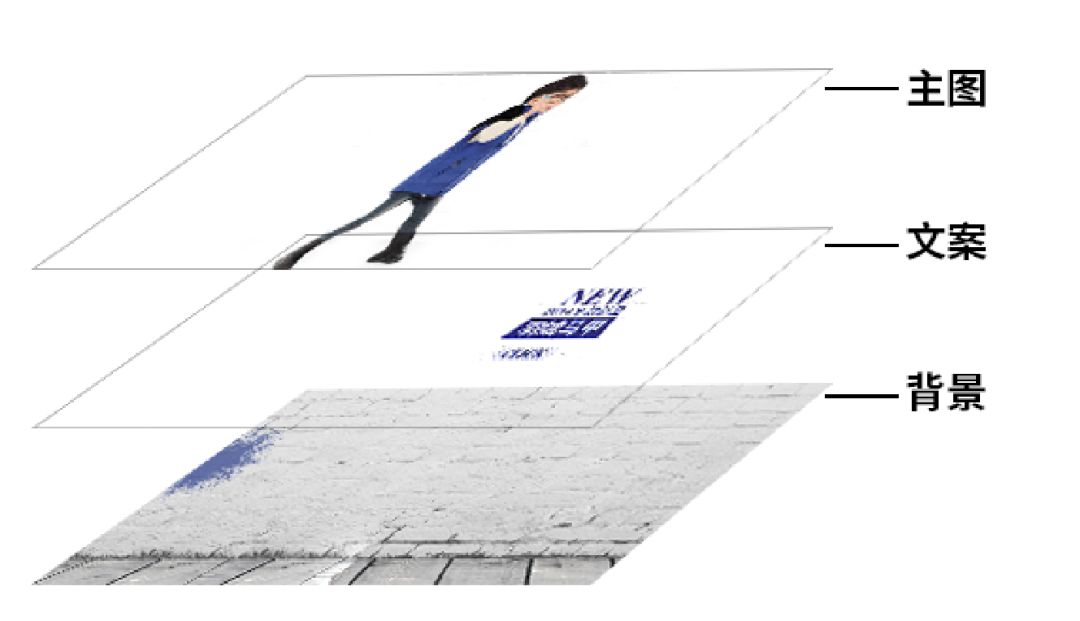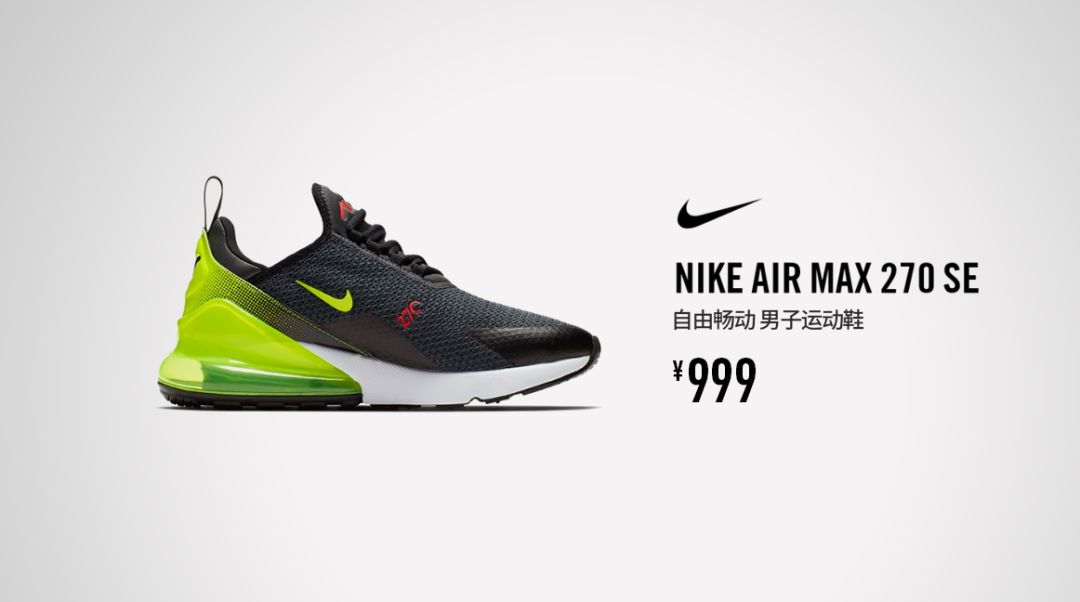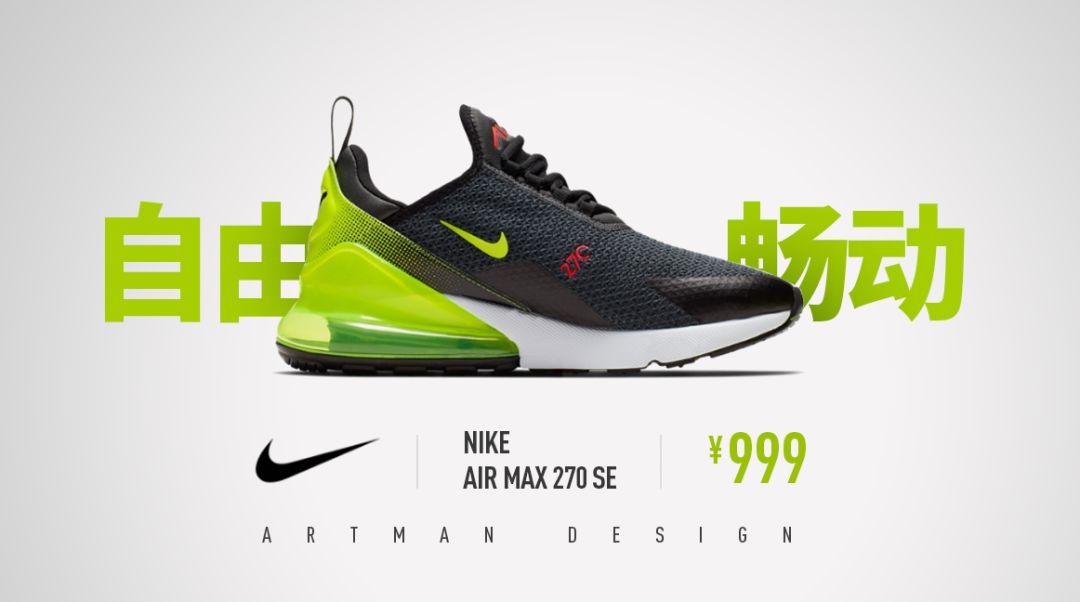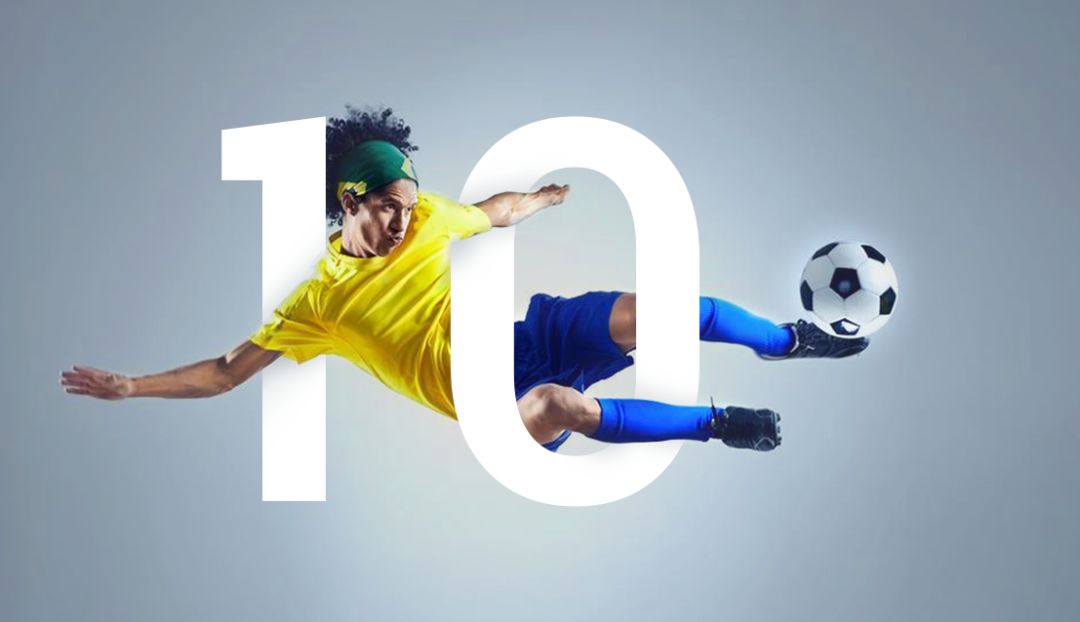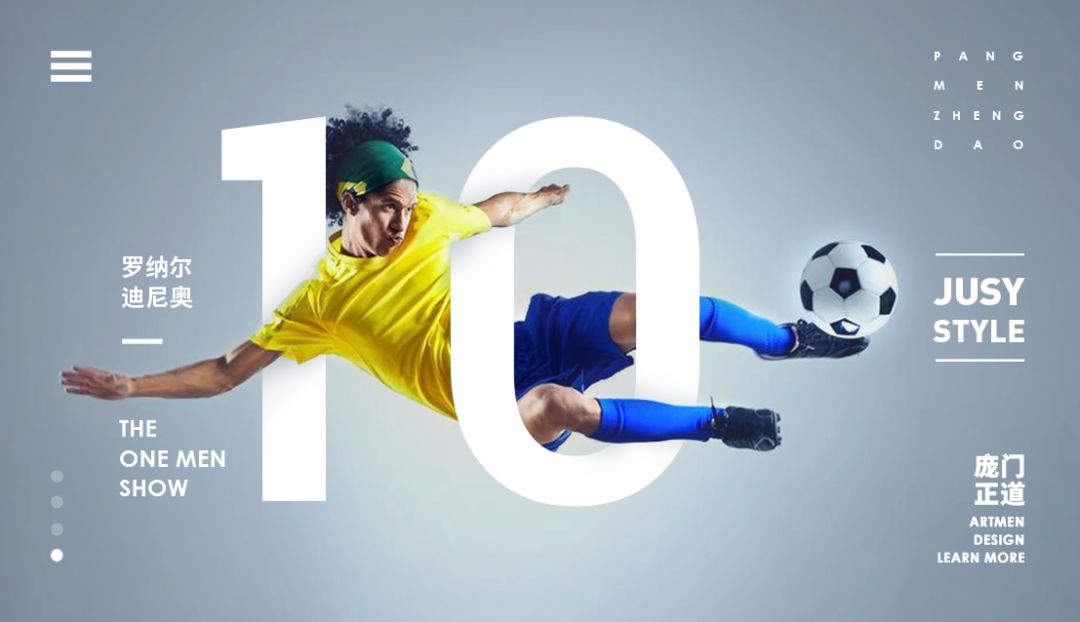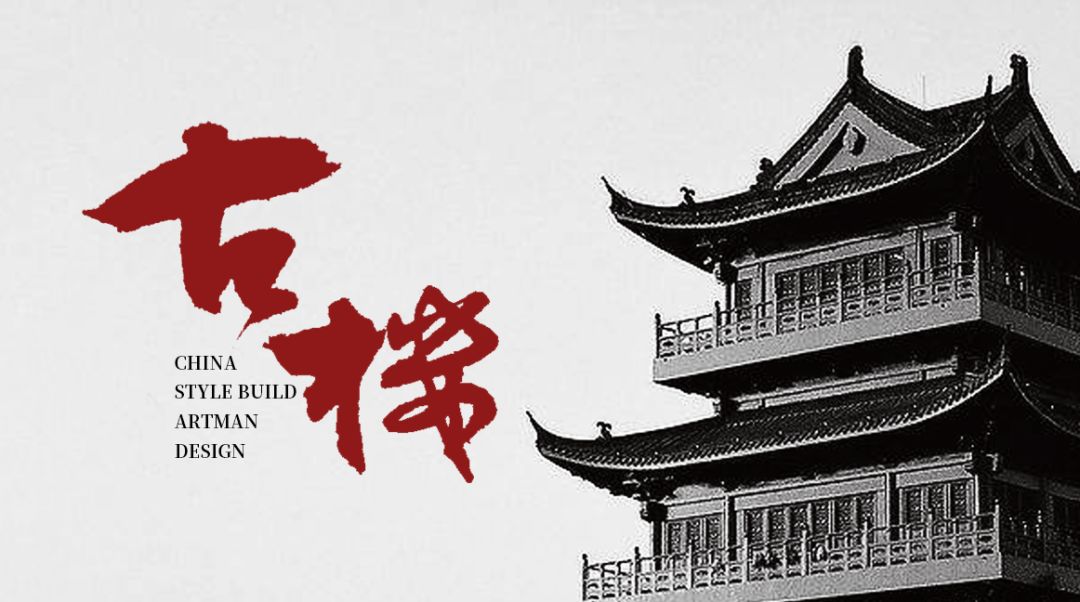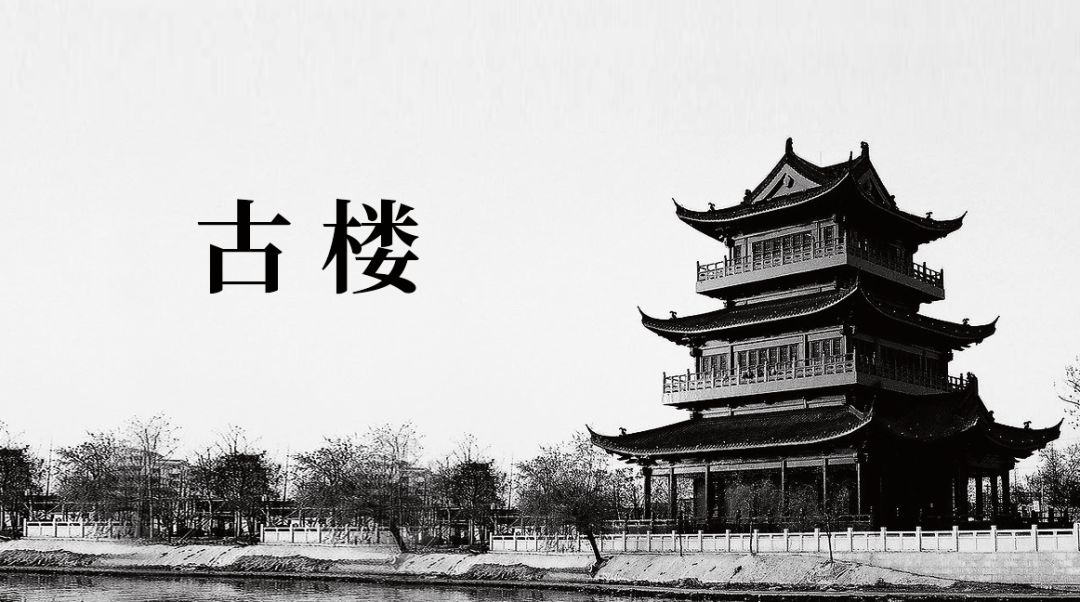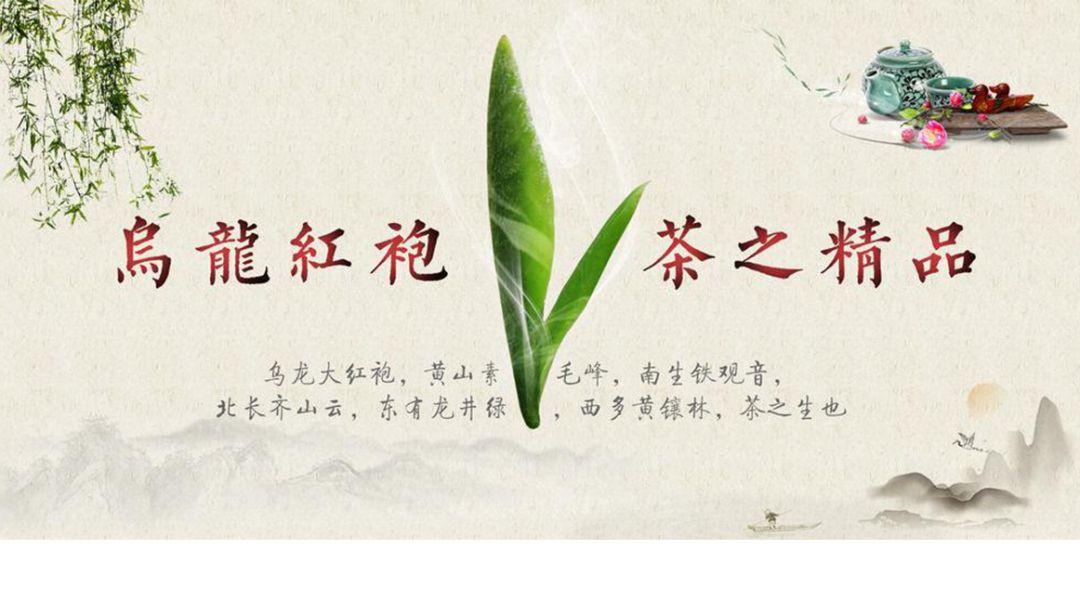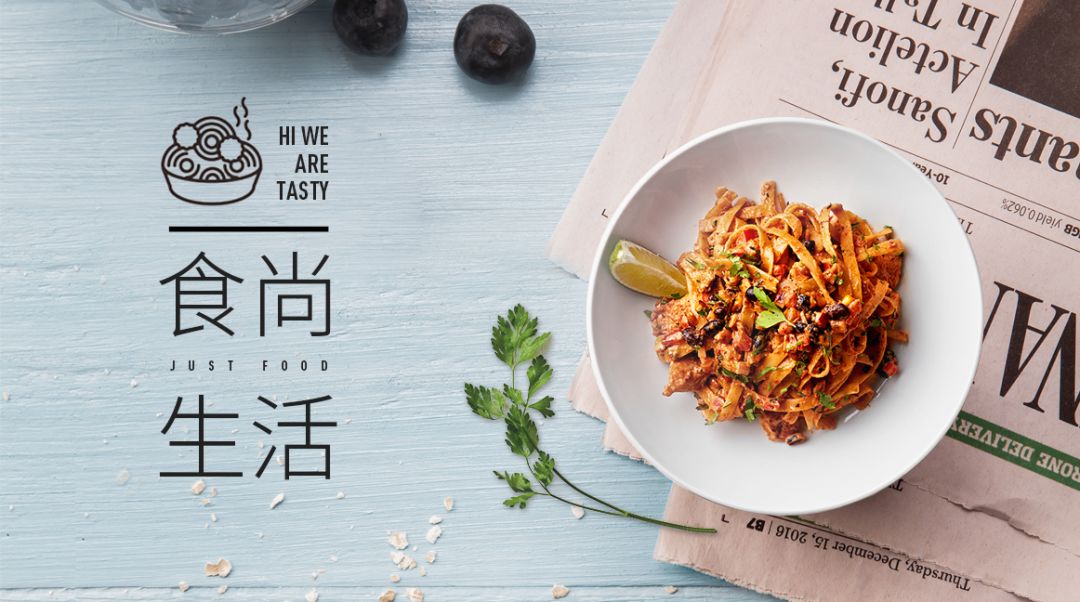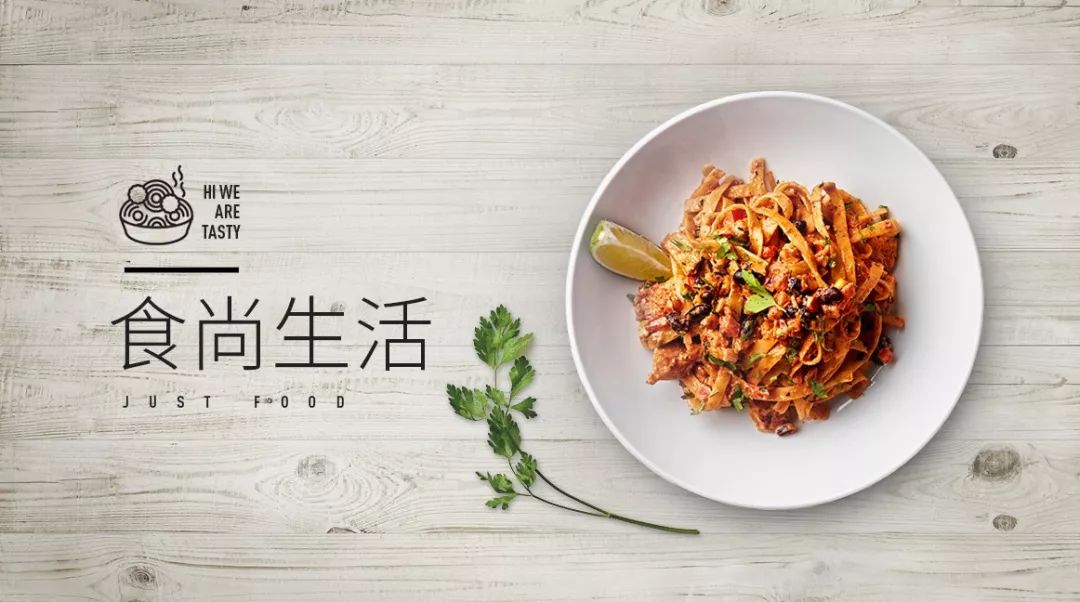
设计中说的留白到底是什么?
“你这画面空那么多留着跳广场舞吗?”老板指着我的设计图问道!
这种经历大家都有吧?
不过那是从前的事(小地方可能还是这样)。
而这几年随着极简风的流行,让大家都知道了好的设计应该要适当留白,但这也同时让很多新手走入了误区,以为设计必须大量留白。
留白实际上是一个挺难掌握的高级技能,对于很多新手来说,掌握得不好,留白就变成了空白!
画面空,很显然是由于画面元素太少,或者比例不对所造成的。空白过多会让画面显得很单薄,没有视觉冲击力,缺乏设计感。
所以,强行把空白解释成留白是不对的。
好了,分清了留白与空白的关系之后,我们就来看看有哪些方法可以解决画面太空的问题。
新手设计师们在做设计的时候,都是按部就班的把文案、主图、背景拼在一起,然后就duang的一下,完工了!
最后的成品就像这样:
看起来好像没啥大问题?
颜色协调,主体突出。
唯一的问题就是。。。有点空。
如果再深入的思考一下,这个画面除了有点空之外,更重要的是,元素之间并没有形成很好的呼应关系,它们只是被生硬的拼凑在一起。
元素之间的孤立,会让画面形不成整体感,最后造成的结果就是画面显得很空洞。
那要怎么解决这个问题呢?
我们都知道画面主要由三类设计元素构成:文案、主图、背景。
如图所示:
既然这样,那我们就从这三大要素入手,一一分析下有哪些方法可以使得画面显得更饱满、丰富。
大家看我的表演!
文案是所有设计元素中,使用起来最灵活的元素。因此,文案的处理对排版的基本功要求很高。
如果画面太空,我们通过下面三种方式来处理文案,使得它可以更好的填充画面。
这三种方式分别是:
大字
小字
背景字
分别通过具体案例来说明一下。
大字:
在画面中使用大字,不但能很好的填充满画面,同时也可以有效的加强画面的视觉冲击力。
比如说下面这张图,中规中矩的排版,画面略显空洞:
我们提取跟产品特性最相关的重点文案,用大字号将它凸显出来,运动的氛围一下就强化不少:
再来看一个例子。
下面这张图颜色和排版都是中规中规的,没啥大问题,就是很难给人留下印象。
我把品牌名称的四个字母做了放大处理,这样就形成一种独特构图形式,再将文点作为点缀元素加进,画面一下就丰富起来了。
怎么样,大了之后是不是有意想不到的效果!
(这么简单都学不会还吃吃吃?)
说完了大,我们再来看看小。
小字:
小字跟大字不一样,它起到的是辅助作用,小字可以让画面更加的层次丰富。
比如说这个例子:
加上一些小字之后,不但画面更平衡了,视觉上的层次感也更丰富。
再看个例子:
见缝插针的加入一些小元素。
这里的小字,你可以理解为辅助小元素。适当的添加一些小元素,不但能让避免“空”的感觉,还能让画面看起来更精致。
接下来看一种特殊的文字。
背景字:
背景字就是将文字完全图形化,作为装饰元素放在画面中。
下面这张图的问题同样是简洁过了头。
在背景上添加summer的水印字之后,整个版式一下就更有活力了。
这里注意,背景字作为一种完全的装饰性元素,切记不要做得过于突出,影响到主要信息。
好了,有了上面这三招,估计你的画面想空都不容易了。
牛不牛?
讲完文字部分,接下来说下图片。
在任何时间,图片都是画面的绝对焦点。因此除了要保证图片本身的质量之外,图片的大小比例,以及风格统一也非常重要。
我们通过案例来具体说明。
比例适当:
在将一张素材图片放到画面中时,首先要考虑的是什么?
当然是大小比例。
这张图从空白占比来看,不算空。但是正如我前面所说,因为图文之间缺少关联性,所以会造成一种“感觉上的空”。
我把图片重新裁剪一下,再换一下字体,马上就有了浓浓的人文历史感。
虽然空白面积的占比可能更大了,但是画面却更饱满!
例如一张这样的成品,其实是。。
原图是这样。。
我要了其中一部分而已,这样去掉多余的部分,也不能较多余,把不想要部分去掉就对了。
风格一致:
除了适当的比例之外,画面中图片风格也需要保持一致性。
下面这张图里用到的图片素材多达四五种,栁叶、茶叶、茶壶、水墨背景这些素材无论是颜色上,还是造型上,都存在着很大的差异,因此它们放在一起完全就是胡乱拼凑。
由于主体图形茶叶的造型不够饱满,所以尽管拿了各种素材来填充画面,但整个画面依然觉得很空。
我将主图形换成了造型和颜色都一致的图之后,虽然整个画面有着大量的留白,但是你会觉得这些留白的存在都是合理的。
所以,将空白变成留白,也是解决画面空洞的一种很好方法。
接上来再看背景的处理方法。
背景其实是决定一个设计风格的基础,但是很多新手往往容易忽视。
在画面不够饱满的时候,许多人都会想方设法的加入更多的视觉元素进来,从而导致画面失去控制。
有时候我们在背景上做做文章,恰恰能收到事半功倍的效果!
下面这张图看起来还不错,图片精致,排版也很工整。
不过作为一张美食广告,好像少了一点食欲,因此我们需要增加画面的丰富度。
在背景上作处理,我们常见的基本就三种方法,分别是:
色彩
纹理
场景
通过例子来说明。
色彩:
通过色彩来丰富画面,是最常见的手法。
强烈的对比色不但可以衬托出食物的新鲜度,增强食欲。同时也能让画面瞬间被填满,完全没有空洞的感觉。
纹理:
纹理虽然没有对比色那样的刺激感,但是它可以有很好的带入感,比如说加了木纹之后,会让你联想到桌子上的美食。
场景:
场景是纹理的进阶版。
它不但有背景纹理,而且会添加许多跟场景相关的细节物件,以强化整个画面的感觉。
比如说桌面上的报纸:
或者餐具,桌布等:
场景化的设计需要注意元素统一的问题。
比如说上面的美食广告,如果你放一个苹果笔记本,那就会显得有点怪异,因为那是办公用品,不应该出现在用餐的场景里。
好了,这期教程内容就到这。
OK,最后回顾一下解决画面太空的几个方法:
一、文字
大字号
小字号
背景字
二、图片
适当比例
风格一致
三、背景
颜色
纹理
场景